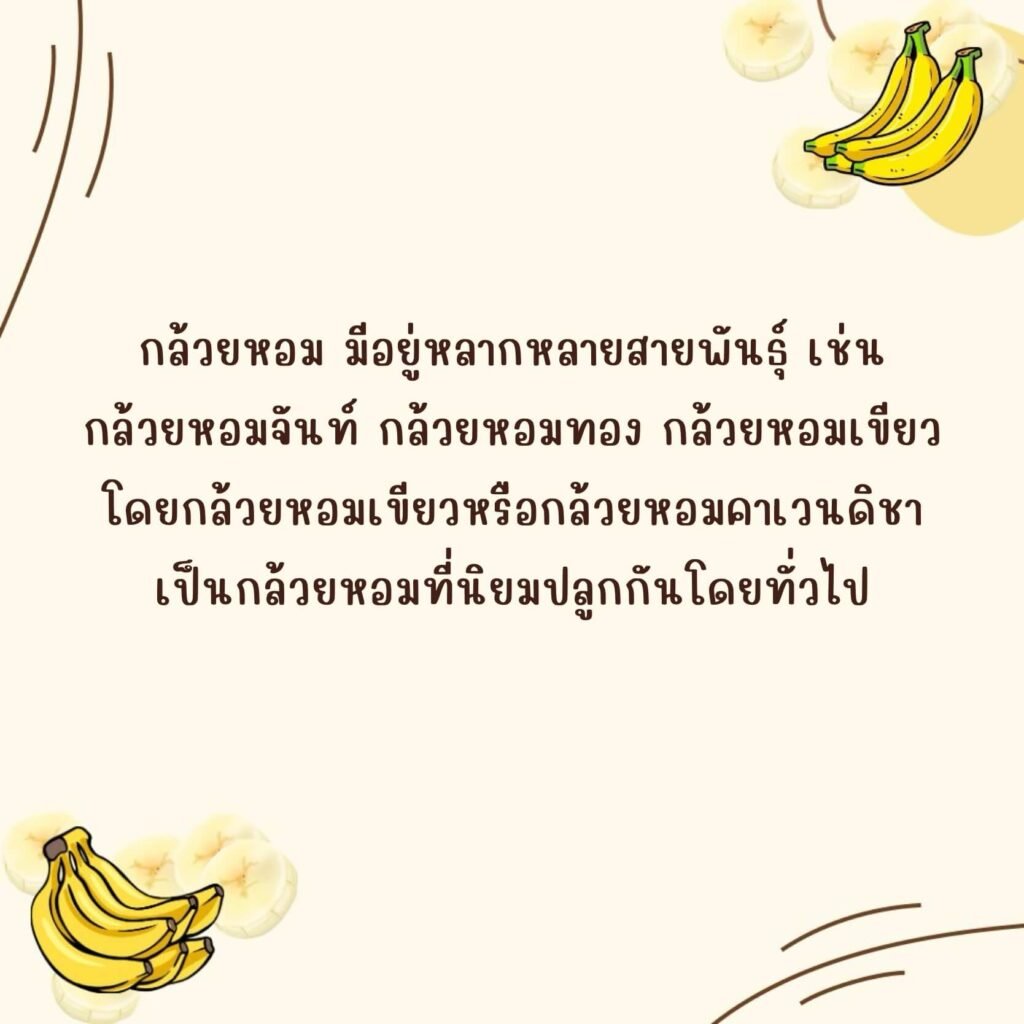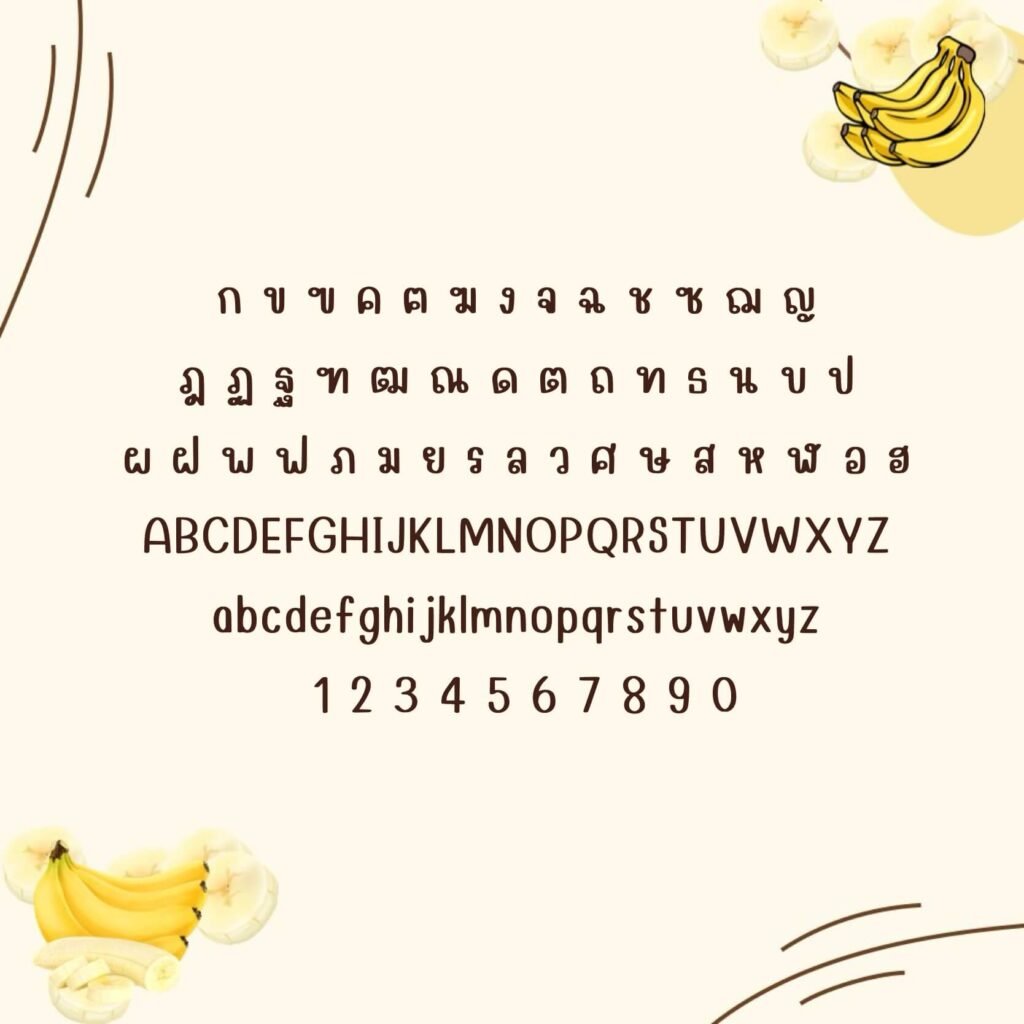
กล้วยหอม (Kluayhom)
แจกฟรี !! ฟอนต์ลายมือ กล้วยหอม (Kluayhom) สำหรับใช้งานที่ไม่เกิดรายได้ 1 น้ำหนัก (บาง) เป็นฟอนต์ที่สามารถใช้งานได้หลายรูปแบบ ไม่ว่าจะเป็นจดโน้ต สรุปงาน